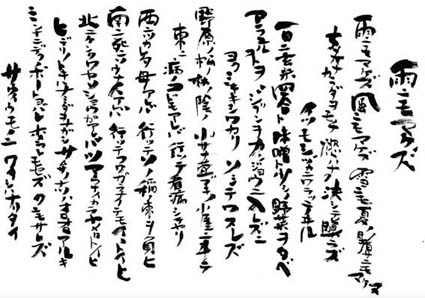
文字屋初の長文作品のご依頼でした。書いているうちに文章を覚える事ができ、心が穏やかにかつ自然で行こうと感じるようになりました。この詩は宮沢賢治が自分に対して思う事を綴っただけであり、決して他人へのお説教ではないと思います。なので、あまりしっかり書き過ぎないよう、多少ふわふわしながらも強さのある雰囲気に仕上げるよう心掛けました。文を覚えるほどに、ノリノリで書いていけるのはいいのですが、ひらがなを入れてしまって何度も書き直した、思い出の作品です。 <ヨロコビの声> |